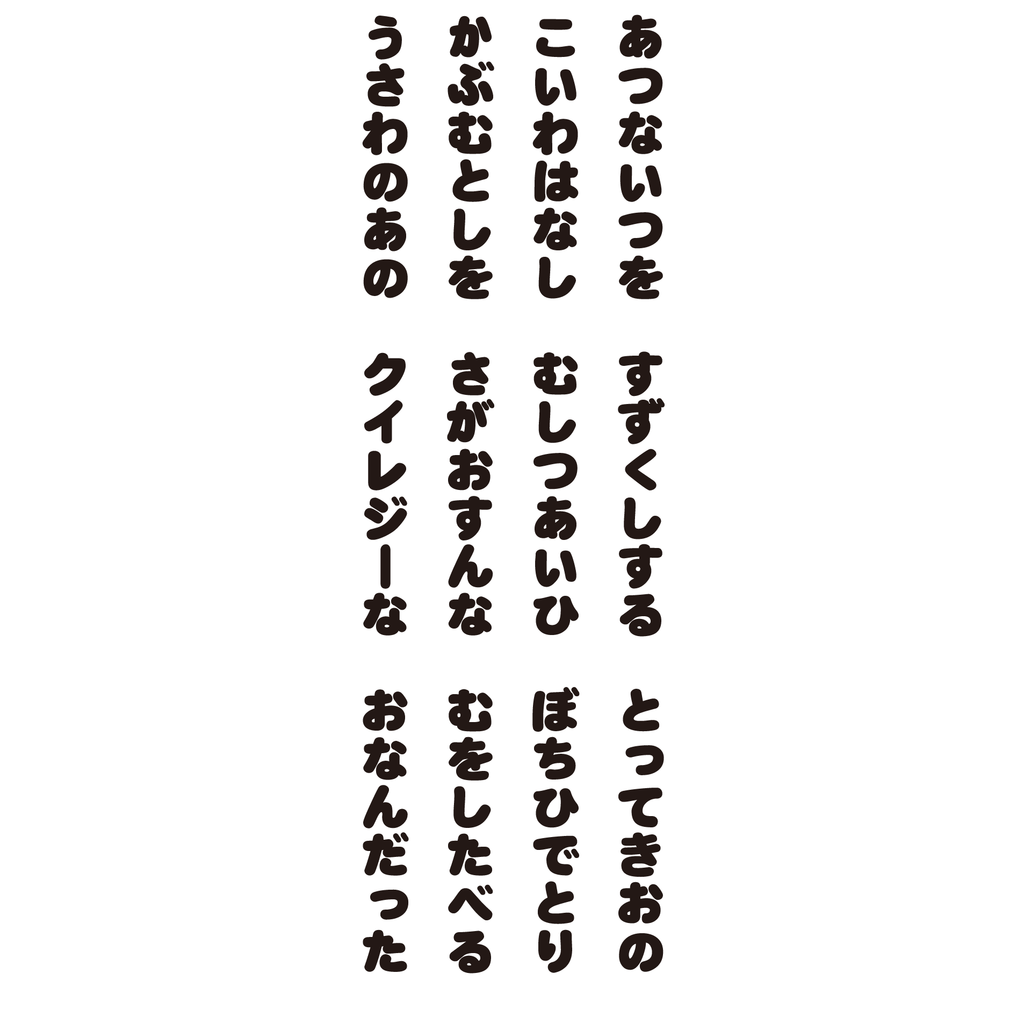
超極太丸ゴシック体
超極太丸ゴシック体は超極太な太さを持つ丸ゴシック体。
シンプルかつ洗練されたゴシックをベースに、起筆と終筆及び転折に弧を描くような曲線でデザインすることで、全体に柔らかな雰囲気をもたらした親しみやすさがある。
極太丸ゴシック体より更に太いストロークになっている。
超極太丸ゴシック体と極太丸ゴシック体の太さを比較
ダイナフォントには極太丸ゴシック体というフォントもある。そこで超極太丸ゴシック体と太さを比較してみた。